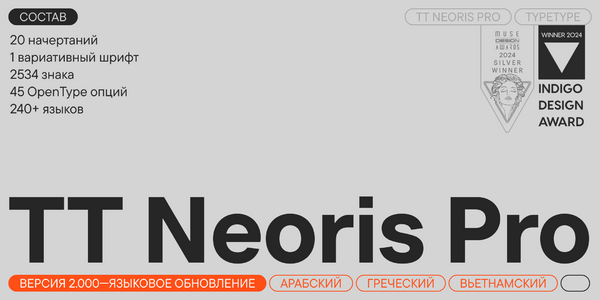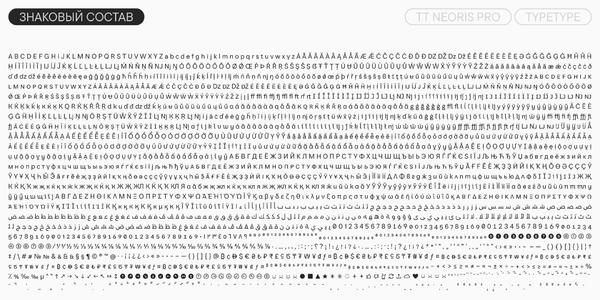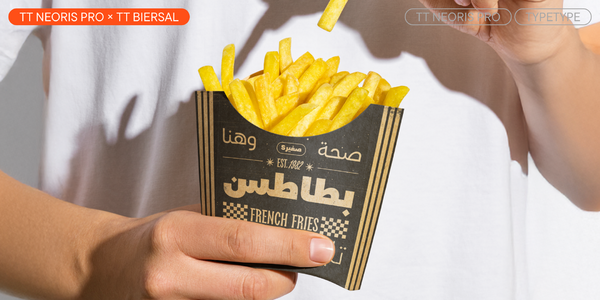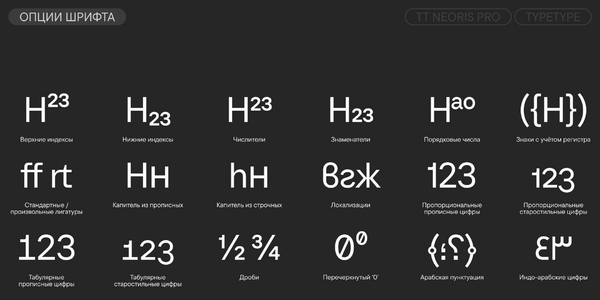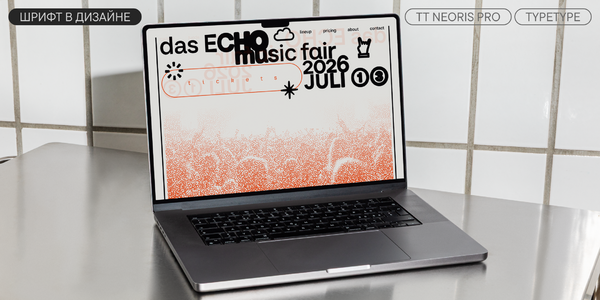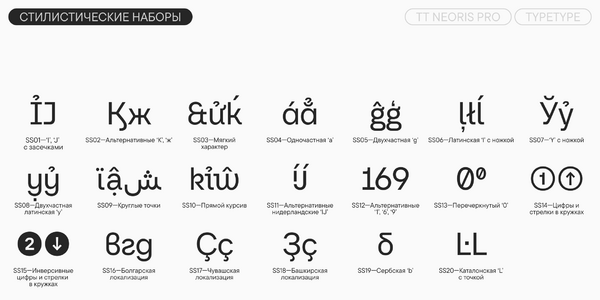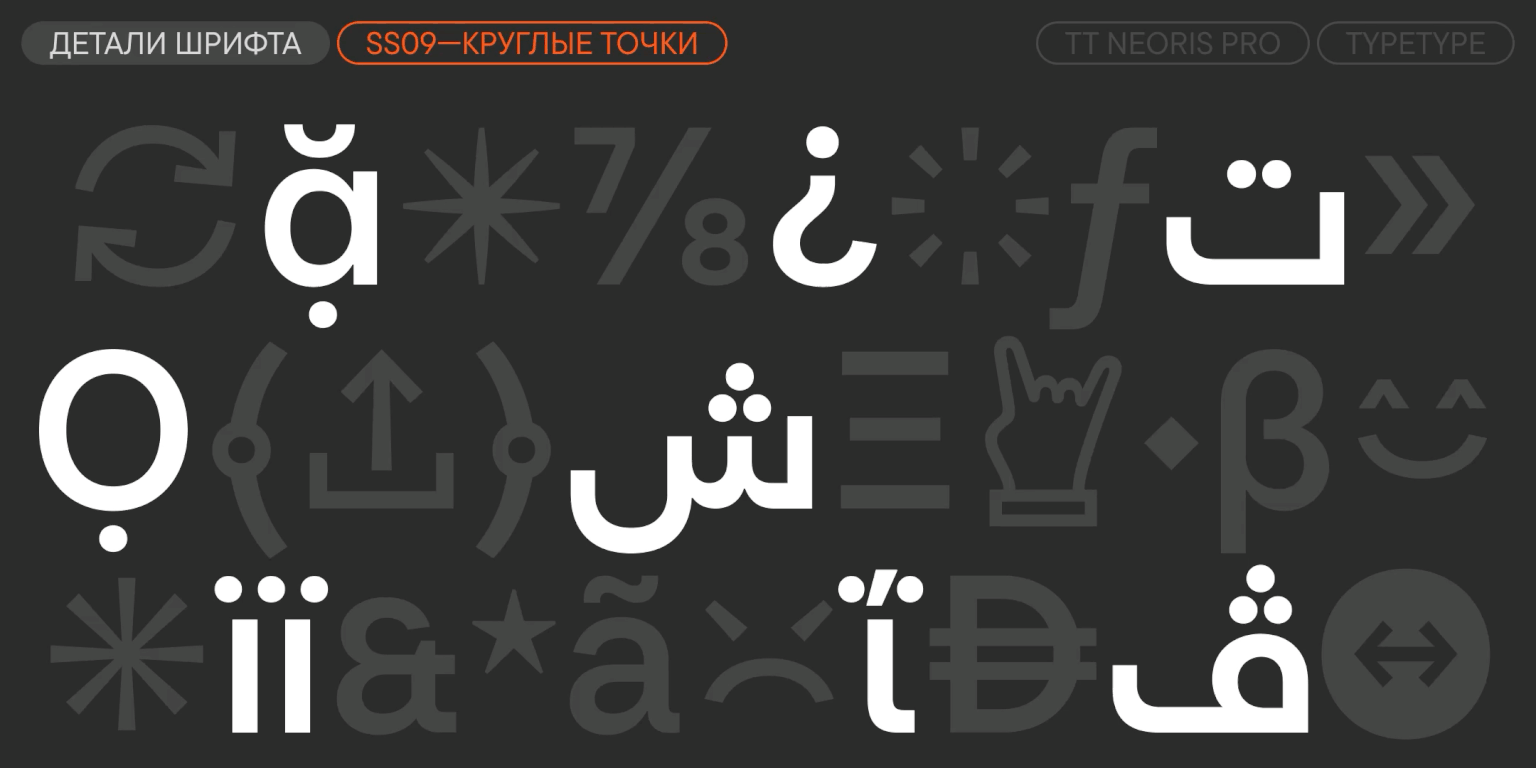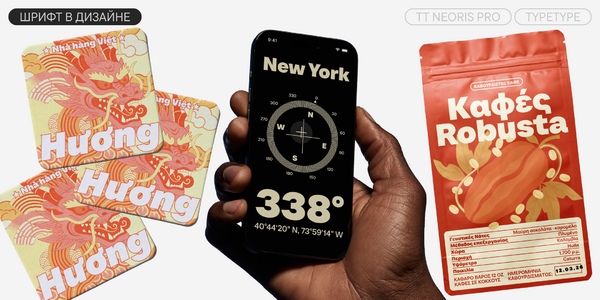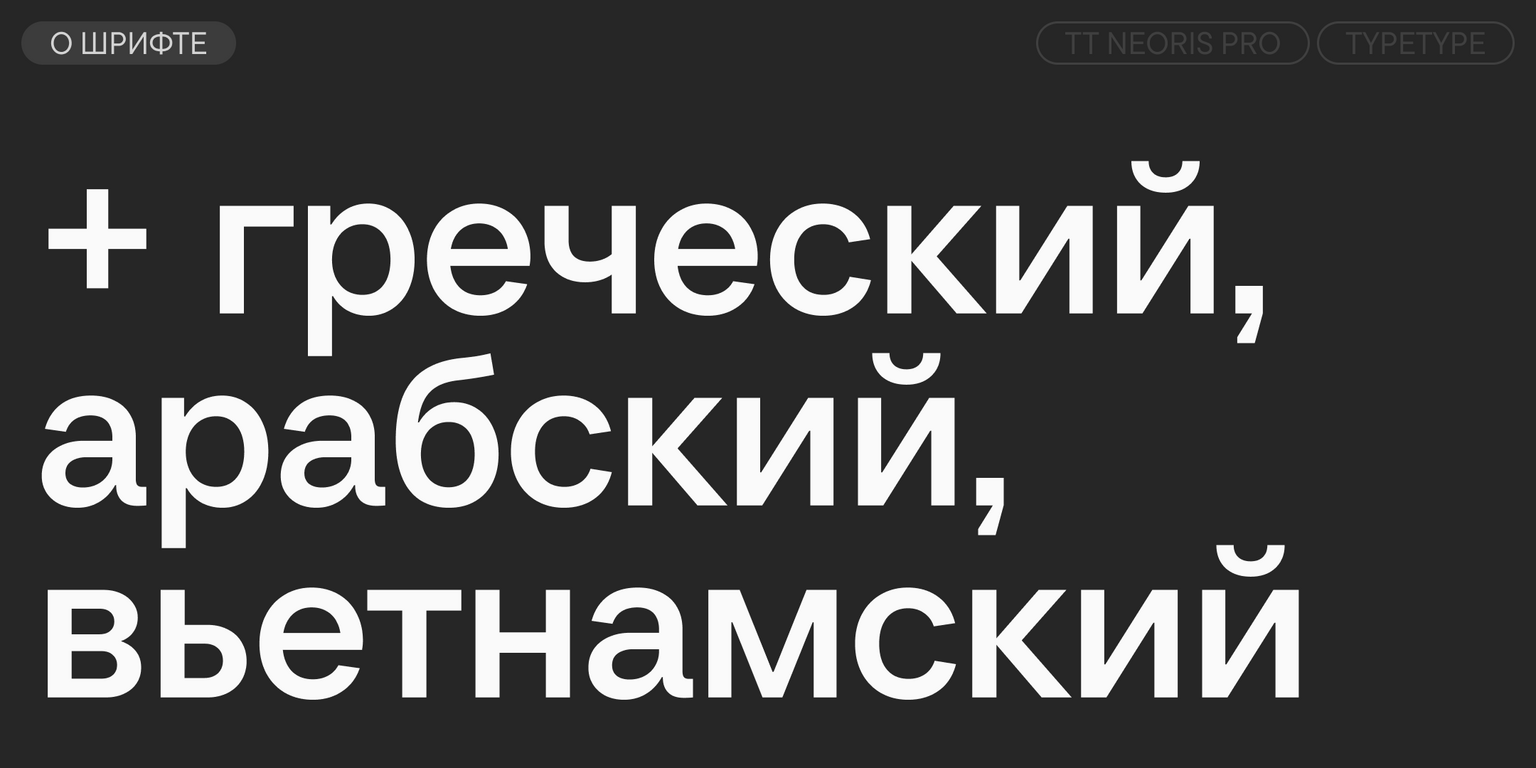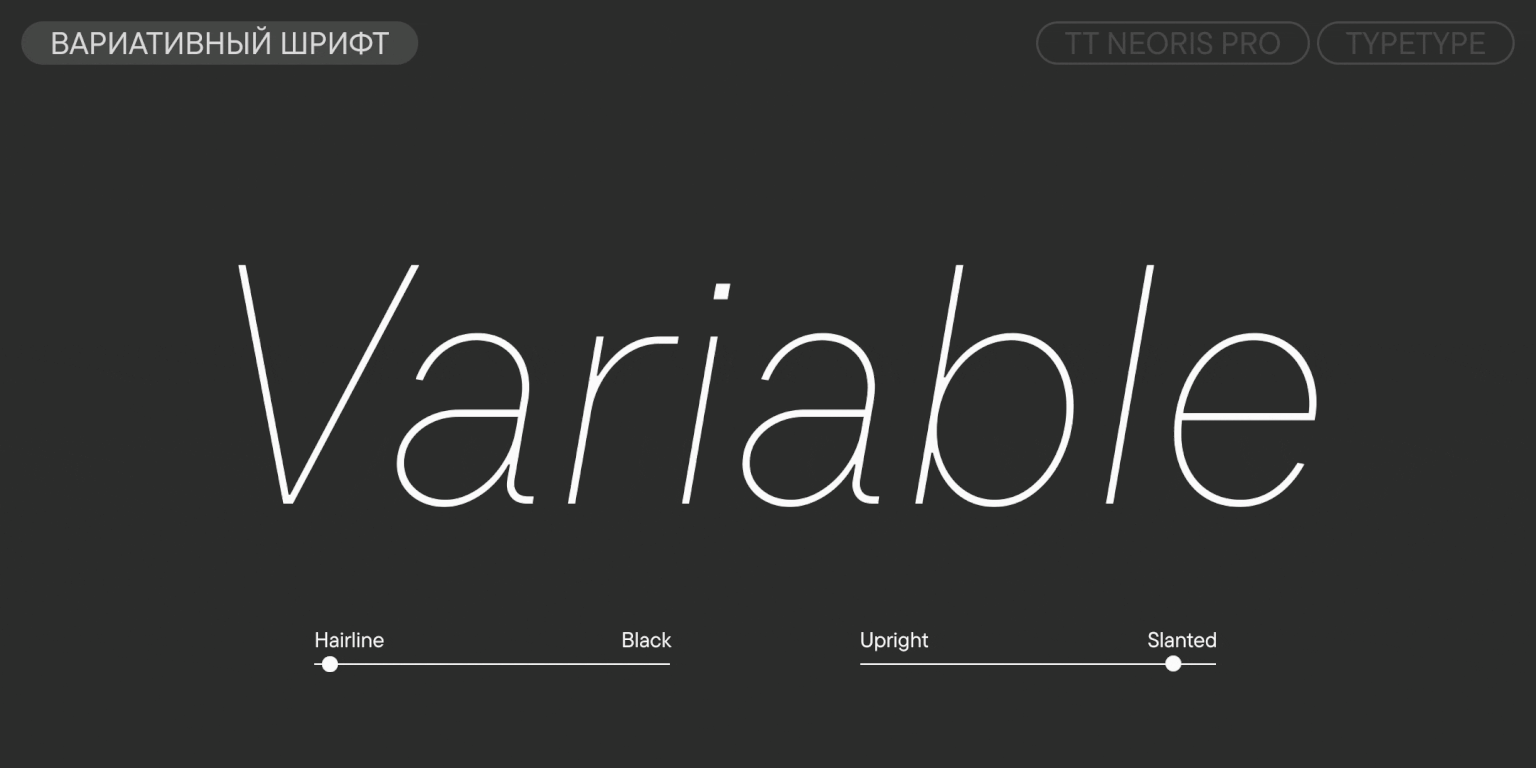
21 стиль
TT Neoris Pro — ТТ Неорис
Произносится «ТТ Неорис». «Neoris» — производное слово от neo («новый» с латинского) и rise («восход» с английского). Буквы «TT» являются аббревиатурой названия компании.
TT Neoris — неогротеск для универсального использования
Мы разрабатывали шрифтовое семейство TT Neoris в течение 2,5 лет. Первые четыре месяца работы изучали рынок шрифтов, и в результате подготовили фундаментальное исследование на тему «Идеального гротеска». Каким должен быть универсальный и удобный шрифт для нужд современного дизайна? Какие формы знаков наиболее архетипичны в современном шрифте? Какой знаковый состав должен быть у универсального неогротеска? В процессе исследования мы ответили на эти и многие другие вопросы. В рамках первых эскизов мы искали характер будущего шрифта, ведь именно он определяет весь проект. На начальных этапах проектирования мы старались добиться серьезности самого жирного начертания, при этом сделать его рисунок полностью тождественным регулярному. Далее были месяцы кропотливого труда над шрифтовым семейством — и это была самая сложная работа, которую мы когда-либо проделывали.
Простой, выразительный, понятный, универсальный
2900 часов работы над проектом
Вариативность
Жирность
Наклон
О гарнитуре TT Neoris Pro
Поддержка языков 240+
Встречайте TT Neoris Pro версии 2.000 — теперь с поддержкой греческого, арабского и вьетнамского!
TT Neoris Pro — лаконичный неогротеск (эволюция классического гротеска с более проработанной пластикой и читаемостью) для универсального использования. Мы разрабатывали это шрифтовое семейство два с половиной года. Для начала тщательно изучили рынок и провели масштабное исследование на тему «идеального гротеска». Затем, опираясь на результаты, поставили перед собой задачу — создать неогротеск с нейтральным характером, базовый и удобный в использовании, при этом оригинальный, актуальный и свежий.
Именно таким и получился TT Neoris Pro: простым и выразительным, универсальным и функциональным. А ещё — разносторонним и многоголосым. Благодаря большому количеству опций один этот шрифт способен заменить собой сразу несколько, меняя настроение и характер.
Мы уделили особое внимание деталям, чтобы приблизить шрифт к идеалу. Сделали пропорции наклонных начертаний немного более узкими, чем прямых, и добавили стилистический набор с формами настоящего наклонного шрифта для кириллицы — его рисунок соответствует традиции кириллической каллиграфии. Добились, чтобы у самого жирного начертания был такой же серьезный характер, как и у регулярного. А ещё добавили поддержку всех языков на основе кириллицы, у которых более миллиона носителей.
Главным обновлением в версии 2.000 стало появление греческого и вьетнамского языков, а также шрифта на основе арабского алфавита. Все формы выглядят подчёркнуто нейтрально и актуально. Для арабской версии мы выбрали гибрид стилей куфи (геометрический, угловатый стиль арабского письма) и насх (округлый, курсивный почерк арабского письма для повседневного использования) — это современная версия арабского шрифта с довольно простой и минималистичной графикой, но с небольшими гуманистическими ходами, которые заметны в терминалах и влитиях. Главной фишкой стали ромбовидные точки во всех диакритических знаках, которые можно заменить на круглые с помощью стилистического набора.
Также мы добавили знаки валют дирхам и донг во всех регистрах, обновили кернинг (избирательное увеличение или уменьшение интервала между двумя символами, обусловленное сочетанием их форм) и хинтинг (оптимизация шрифта для достижения максимальной читаемости на экране компьютера).
TT Neoris Pro 2.000 — это:
• 21 начертание: 10 прямых, 10 наклонных и 1 вариативный шрифт, меняющийся по осям жирности и наклона;
• 2534 знака в каждом начертании;
• 45 OpenType опций;
• 20 стилистических наборов;
• Поддержка 240+ языков.
Что изменилось в шрифте:
• Количество знаков в каждом начертании увеличилось с 1832 до 2534 — в частности, появились знаки валют дирхам и донг во всех регистрах;
• Количество OpenType опций выросло с 41 до 45;
• Количество языков увеличилось с 230+ до 240+ — в частности, появились греческий и вьетнамский языки, а также шрифт на основе арабского алфавита;
• Обновилась техническая сторона гарнитуры (кернинг и хинтинг).